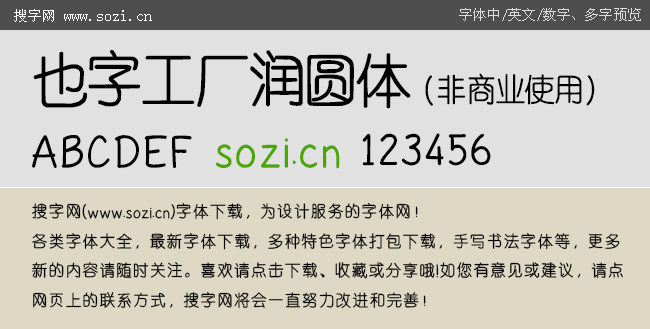
也字工廠潤(rùn)圓體
搜字網(wǎng)給大家提供一款也字工廠潤(rùn)圓體(非商業(yè)使用)中文字體下載,也字工廠潤(rùn)圓體是一款圓體字體,字體簡(jiǎn)潔自然,筆畫轉(zhuǎn)折處帶有圓角,具有很好的視覺(jué)效果。適合應(yīng)用于海報(bào)設(shè)計(jì)、包裝設(shè)計(jì)、網(wǎng)頁(yè)設(shè)計(jì)等應(yīng)用(此字體為個(gè)人非商用版,商用可以聯(lián)系:官方網(wǎng)址:https://yefont.com/home,聯(lián)系方式:13798980448)。